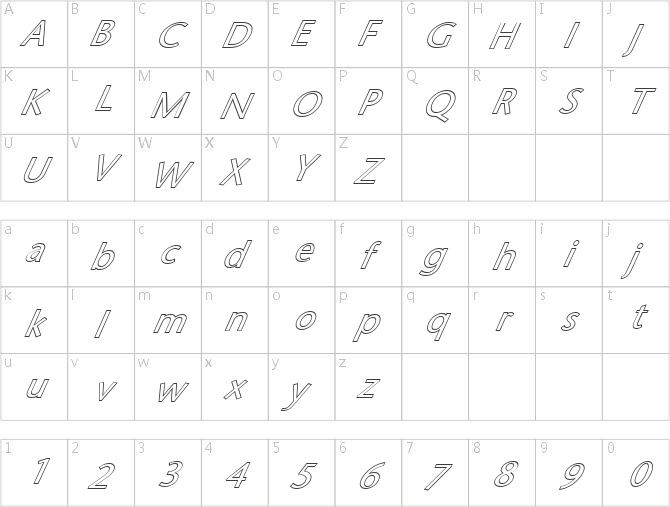
FZ BASIC 25 HOLLOW ITALIC
FZ BASIC 25 HOLLOW ITALIC介紹
FZ BASIC 25 HOLLOW ITALIC字體字庫是一款讓人賞心悅目、百看不厭的英文字體,適合各類廣告和產品包裝設計應用,字體大小0.06MB,格式為ttf字體,上傳用戶是蕪耆蕪,作者/版權方為未知